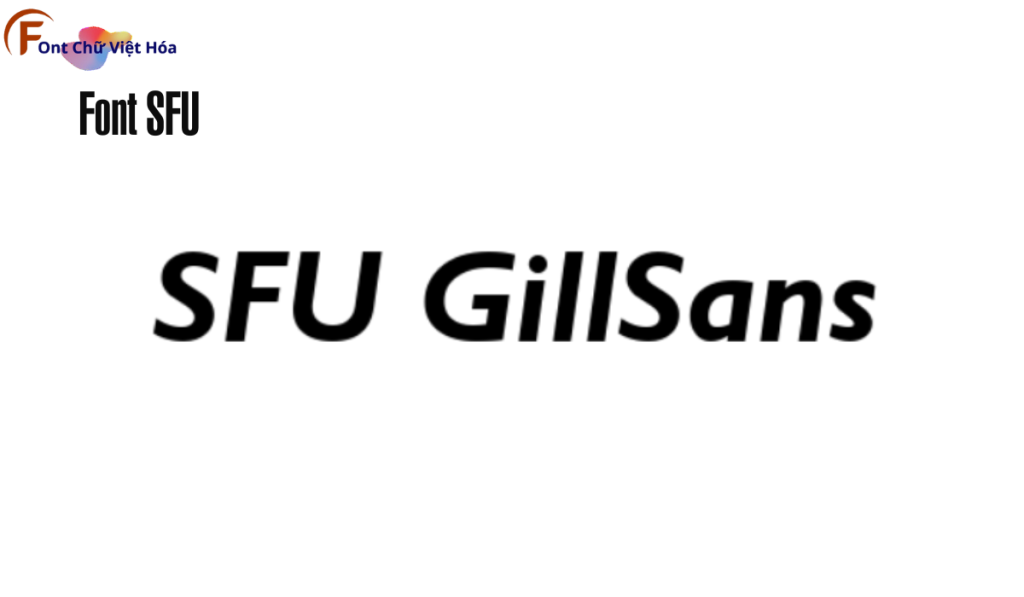
Font SFU Gillsans Việt Hóa
Tác giả: Eric Gill
Bộ Font: SFU
Kiểu chữ: Sans-serif
Độ dày: Regular, Bold, Italic
Font SFU Gillsans Việt Hóa, thuộc bộ font SFU, là biểu tượng của sự thanh thoát và tinh tế với phong cách sans-serif hiện đại. Font này được thiết kế nhằm mục tiêu tạo ra sự rõ ràng và dễ đọc, đặc biệt phù hợp cho các thiết kế như poster, logo, và tiêu đề. Đặc điểm hình dạng của SFU Gillsans là các đường nét sắc sảo và tỷ lệ chữ cân đối, giúp tối ưu hóa không gian và tạo ấn tượng thị giác mạnh mẽ. Font này cũng đã được Việt hóa, mang đến sự linh hoạt và tiện dụng cho các dự án thiết kế bằng tiếng Việt, giúp người dùng dễ dàng tiếp cận và sử dụng.